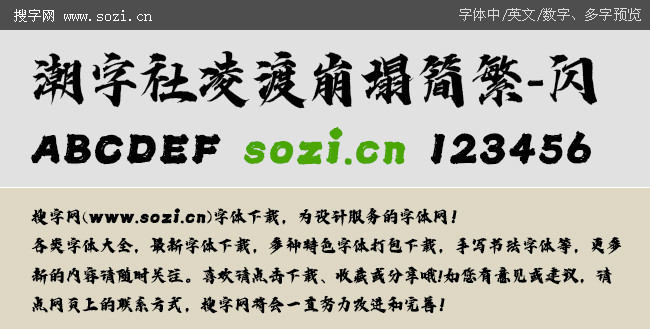
潮字社凌渡崩塌簡繁-閃
搜字網(wǎng)提供一款潮字社凌渡崩塌簡繁-閃中文字體下載,潮字社凌渡崩塌簡繁是一款非常獨特的個性毛筆藝術字體,這款字體筆觸較為粗實,字體書寫端正大方,適合應用于藝術設計、平面宣傳設計、網(wǎng)頁設計等領域等應用。(本字體為個人非商用版,商用請聯(lián)系作者購買授權)